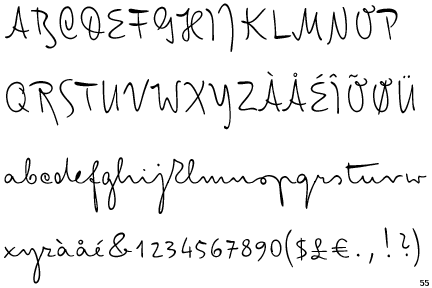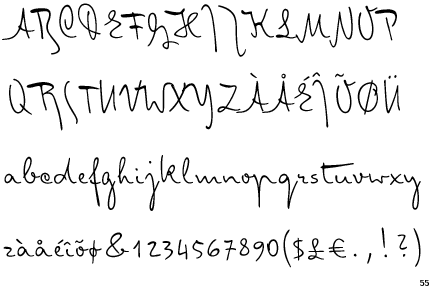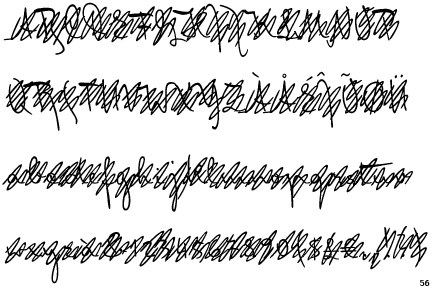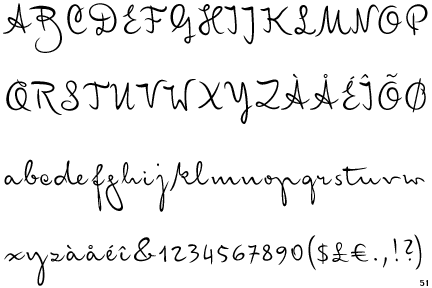
Dichter-Handschrift
ich muss für ein Buchprojekt ein Gedicht so setzen, dass es wirkt, als hätte der Dichter das Gedicht handschriftlich niedergeschrieben.
Dazu bräuchte ich also eine Schrift, bei der einzelne eigentlich gleiche Buchstaben immer wieder anders aussehen und sich der Buchstabenabstand zwischen 2 gleichen Buchstabenpaaren auch immer wieder ändert.
Ich habe keine Ahnung ob es eine solche Schrift gibt bzw. ob das technisch überhaupt möglich ist.
Vielleicht kennt ja jemand eine solche Schrift - müsste wie gesagt eine "Handschrift" sein ... am besten mit der Anmutung einer Schrift eines berühmten amerikanischen Dichters, der das Gedicht im Alter von 60 Jahren Anfang der 60er Jahren mit einer feinen Schreibfeder geschrieben hat.
zapfino hat die Features, ist aber sehr bekannt.
Such mal in der Nähe von Zapfino weiter.
Olicana Smooth & Rough
Olicana Rough now has a milder mannered sister Olicana Smooth, both fonts mimicking true handwriting with pen and ink, complete with finger prints, ink splats and crossings out.
Available in OpenType format covering Western and CE layouts and including swashes, multiple ligatures and stylistic alternates to achieve a truly realistic handwritten effect.
Wenn es um nur 1 Gedicht geht würde ich da einen Kalligrafen beauftragen.
Robert hat grad die Lisa vorgestellt, das könnte dich interessieren.